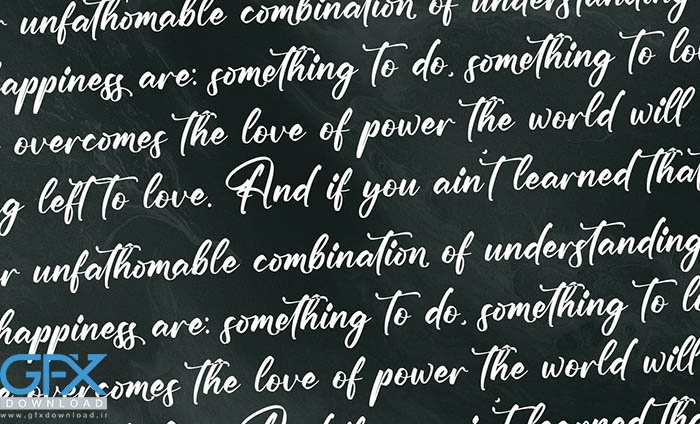
Ratmosh Delliot یک فونت یا قلم مدرن انگلیسی با سبک خوشنویسی بسیار زیبا می باشد که می توانید برای طراحی مارک یا برند تجاری،طراحی کارت ویزیت،پوستر،کارت دعوت و سایر موارد دیگر از آن استفاده نمایید. فونت رایگان خوشنویسی Ratmosh Delliot با فرمت های OTF ، WOFF ، TTF می باشد.
فونت خوشنویسی Ratmosh Delliot